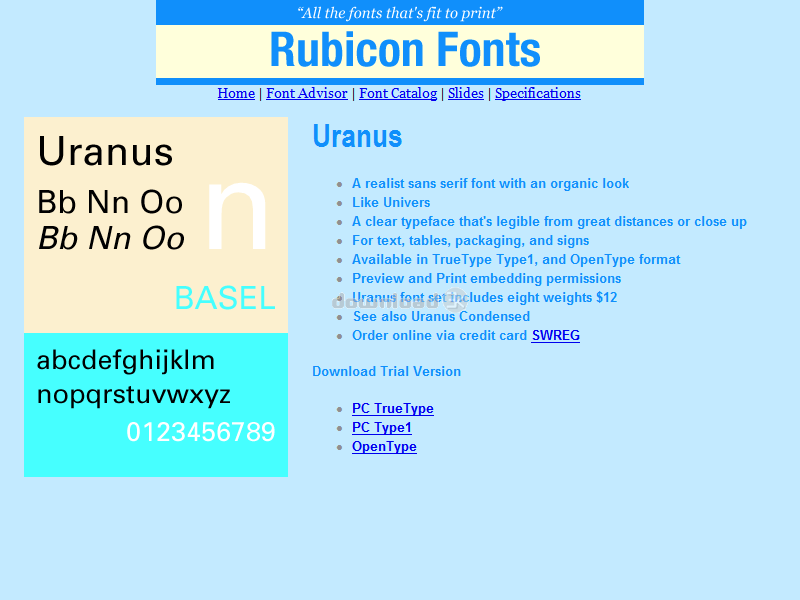
"Реалист шрифт без засечек, органический вид"
Реалист шрифт без засечек с органическими чувствую. Как Univers. Четкий шрифт это разборчиво с больших расстояний или крупным планом. Все цели дизайн, отлично подходит для текста, заголовков, упаковки и знаков. Использование в любой размер. Точная и намекнул, соответствующий шрифт метрик, стандартный набор символов, кернинг пар. Профессиональное качество печати на струйных, лазерных, наборщик до 3500 точек на дюйм. Покупатели получают 8 вариантов шрифта следующим образом: свет, свет Oblique, Normal, Oblique, Bold, Bold Oblique, ExtraBold, ExtraBold Oblique.Требования: Older versions of Windows require Adobe Type Manager.